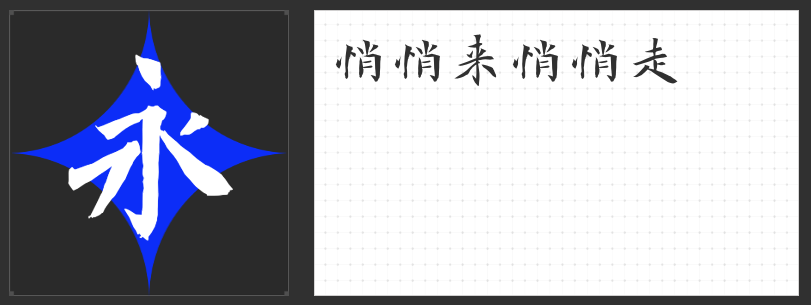
古风字体推荐:四款尽显文化底蕴的绝美之选
在古风文化日益盛行的今天,选择一款合适的古风字体,无疑能为设计作品增添一份独特的韵味。今天,就为大家推荐四款极具特色的古风字体。
1.造字侠今朝醉简
这款毛笔楷书字体,以其收笔潇洒凌厉、如醉酒一般的独特韵味,赢得了众多设计师的喜爱。笔法正统酣畅,劲健雄浑,仿佛能让人感受到书写者挥毫泼墨时的畅快淋漓。它尤其适用于白酒包装等场景,能够完美诠释出白酒的醇厚与热烈。
字体呈扁方形,撇捺向两侧伸展,使得整个字形显得厚重而稳健。收笔前的粗顿以及抬锋,更是为这款字体增添了几分飞扬的动感。规则中正而又富有动态美,使得它在各种古风设计中都能独领风骚。
行书之美,在于其笔画窈窕、秀丽,结构洒脱自然。这款字体用笔圆融,每个字中都有一画或多画点睛之笔,使得字形饱满而富有生命力。无论是用于诗词歌赋的排版,还是作为装饰性文字,都能展现出其独特的魅力。
4.造字侠磅礴简繁
字体中正感官丰富,运笔富有节奏感,呈一波三折之态。笔画粗细变化明显,略有飞白,转折方圆相结合,使得这款字体在视觉上极具冲击力。它适用于各种需要展现力量与气势的设计场景,如书法展览、海报设计等。
这四款古风字体各具特色,无论是哪一款,都能为你的设计作品增添一份独特的文化底蕴和艺术美感。选择它们,让你的设计在古风文化的浪潮中脱颖而出!